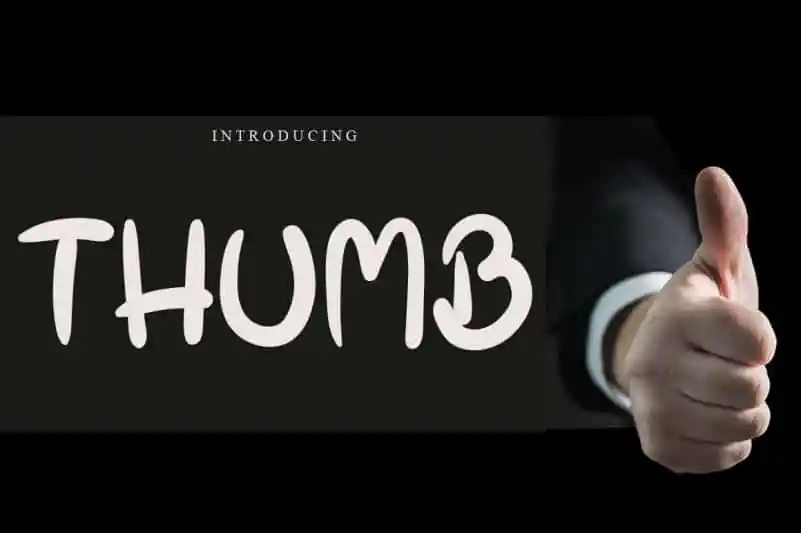
Thumb Display Font – Fonte Grátis
Thumb Display Font
A Thumb Display Font é uma elegante escolha para qualquer projeto que busque aquela nota final especial com uma presença visual imediata e chamativa. Com seu traço sólido e moderno, ela se destaca como um excelente complemento para designs que precisam de um toque único, seja para aplicativos infantis ou criações mais maduros, como posteres, logotipos e capas de livros. Ideal para adicionar uma pitada de sofisticação aos seus trabalhos visuais, especialmente quando você está buscando incorporar elementos humorosos em suas propostas criativas. Com o Thumb Display Font, as crianças podem criar jogos alegres e divertidos usando um texto deslumbrante, enquanto os designers buscam uma maneira de fazer seu trabalho brilhar ainda mais, seja em um livro ou na tela da televisão. Em resumo, essa fonte representa não apenas um recurso gráfico para sua coleção, mas também um passo além no design do conteúdo visual contemporâneo. Esta descrição foi adaptada de forma a ser convidativa e informativa ao mesmo tempo, mantendo o foco na apresentação da Thumb Display Font como uma opção versátil para diversos tipos de projetos visuais. Além disso, ela foi escrita em um tom informacional mais amplo e convidativo, sem entrar em detalhes específicos do designer ou características exclusivas que não foram mencionadas na descrição original.